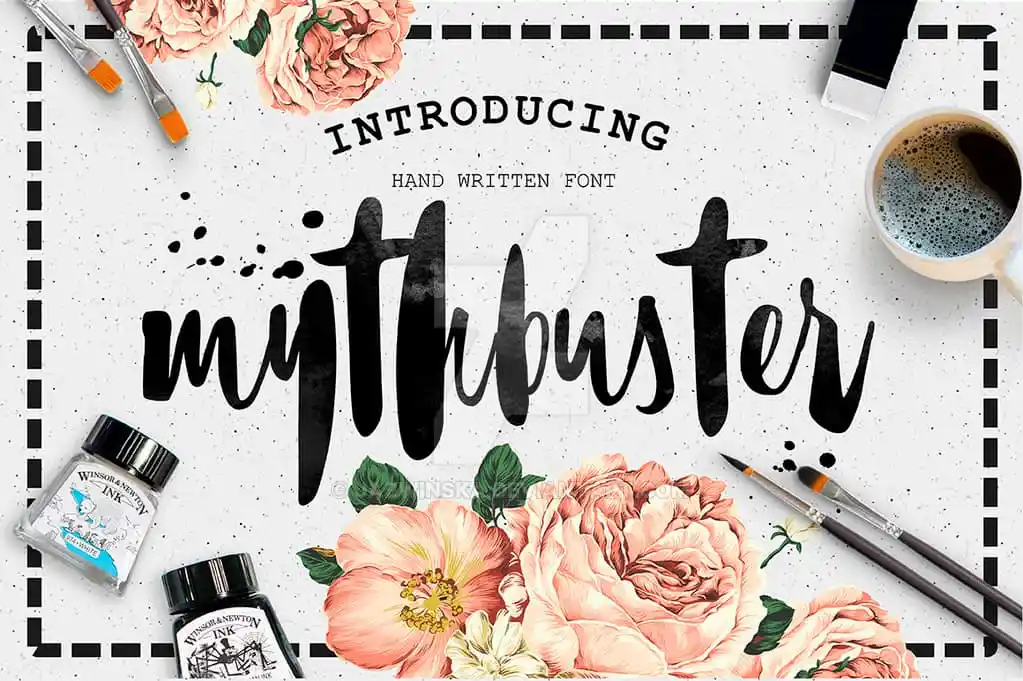
Mythbuster Script Font – Download Grátis
Mythbuster Script Font é uma fonte script moderna que oferece uma aparência fluida e elegante perfeita para projetos visuais variados. Criada por mão dura, esta fonte vem com letras maiúsculas e minúsculas, símbolos de pontuação básicos e números. Suavemente adaptável a qualquer tema desde logotipos até embalagens de produtos, Mythbuster é uma ótima escolha para designers em busca de um acabamento único. Com um design moderno e limpo, essa fonte traz o melhor dos dois mundos entre estética sofisticada e apelo prático. Suas linhas fluidas e sua versatilidade garantem que você possa explorar suas várias aplicações, desde assinaturas de cartão até banners e identidades corporativas. Ideal tanto para aqueles desejando uma aparição delicada quanto para aqueles buscando um visual mais agressivo, Mythbuster é uma fonte de elevar qualquer projeto em sua categoria.